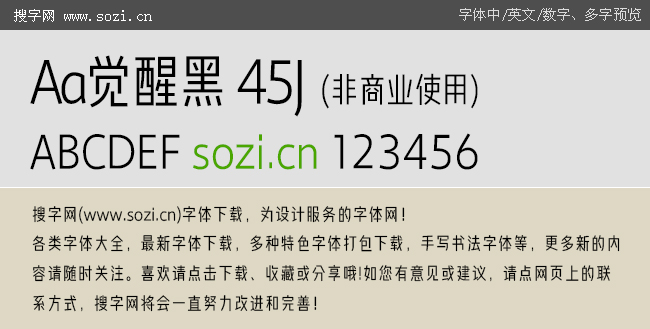
Aa覺(jué)醒黑 45J
搜字網(wǎng)給大家提供一款A(yù)a覺(jué)醒黑 45J(非商業(yè)使用)中文字體下載,Aa覺(jué)醒黑是一款藝術(shù)黑體字體,字體簡(jiǎn)潔大方,字形端正耐看,具有很好的視覺(jué)感,適合應(yīng)用于藝術(shù)設(shè)計(jì)、平面宣傳設(shè)計(jì)、網(wǎng)頁(yè)設(shè)計(jì)、海報(bào)設(shè)計(jì)等應(yīng)用(此字體為個(gè)人非商用版,商用可以聯(lián)系QQ:1006760504)。